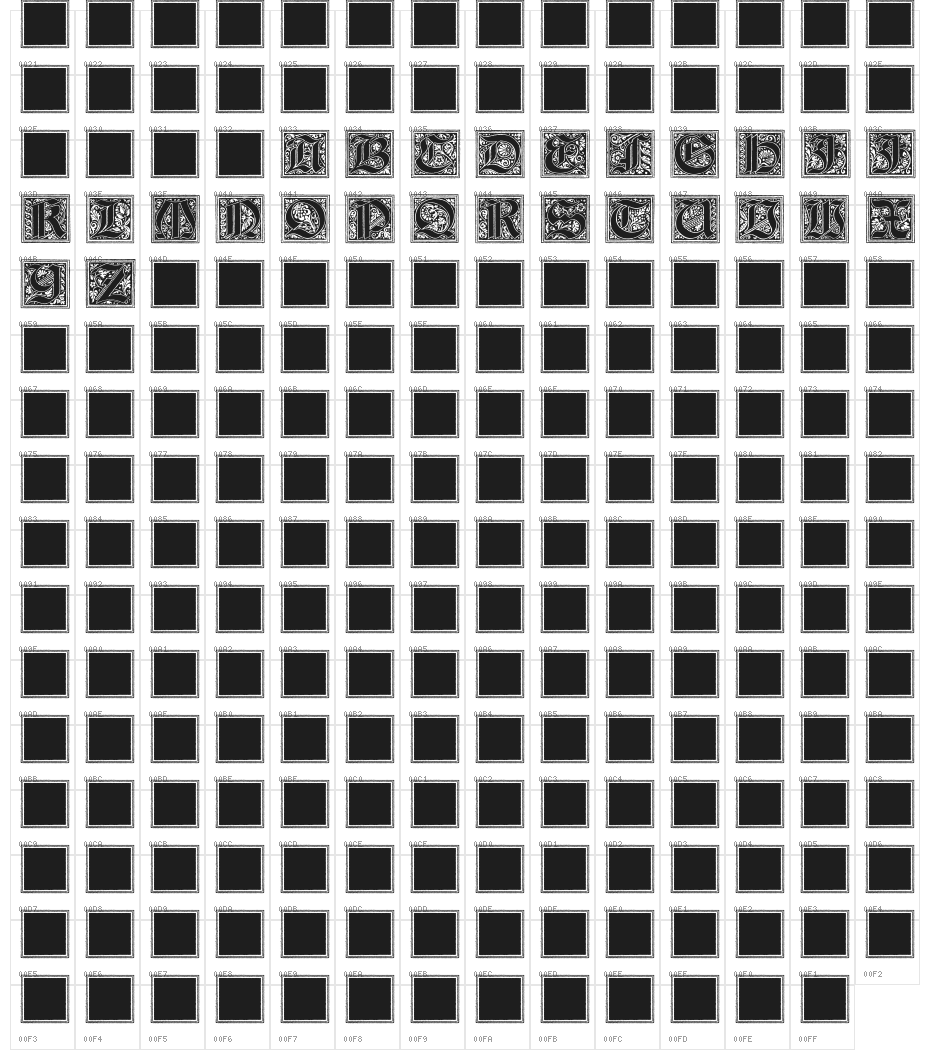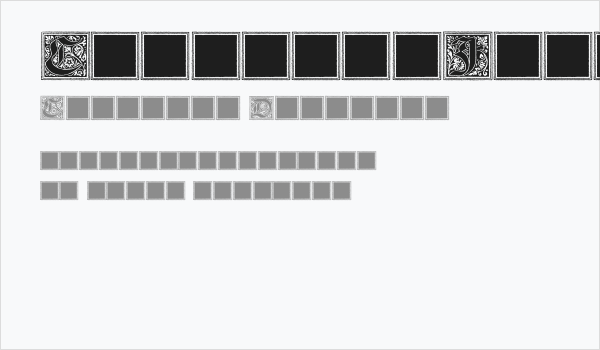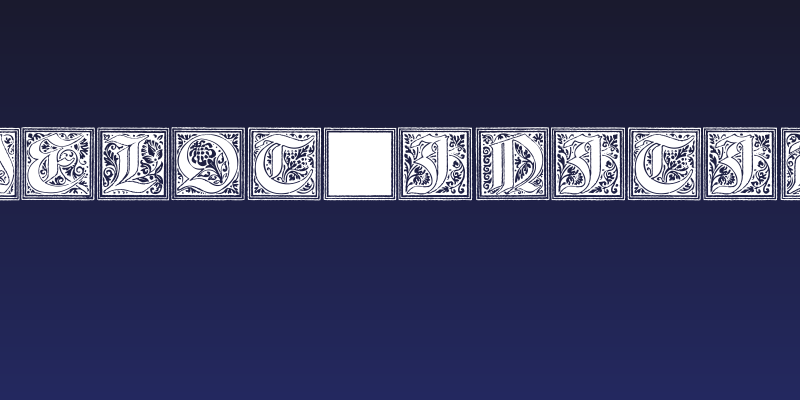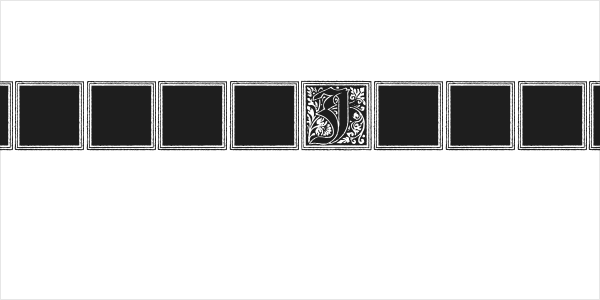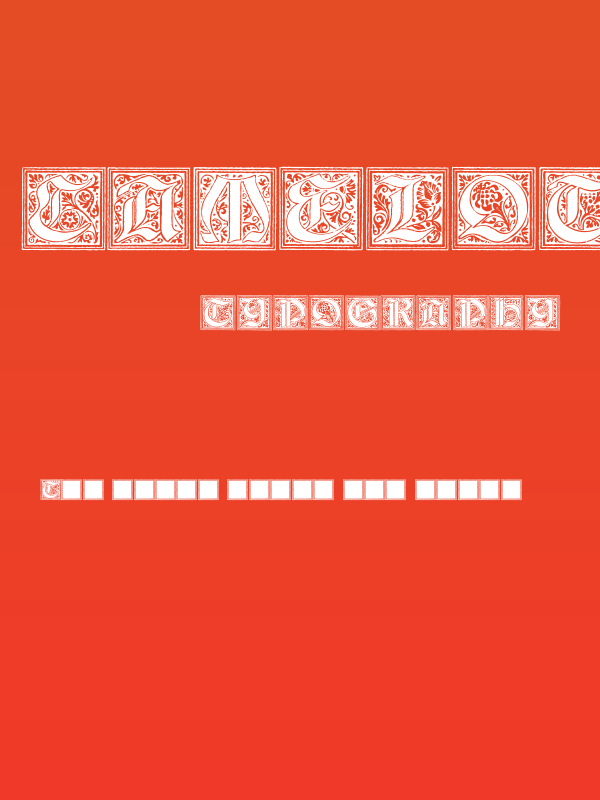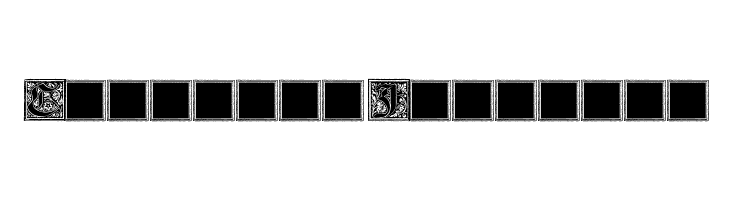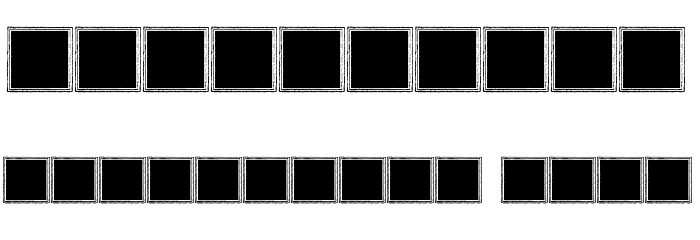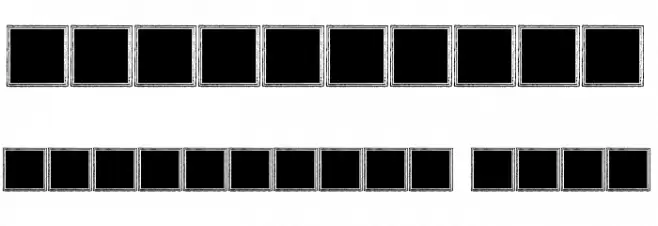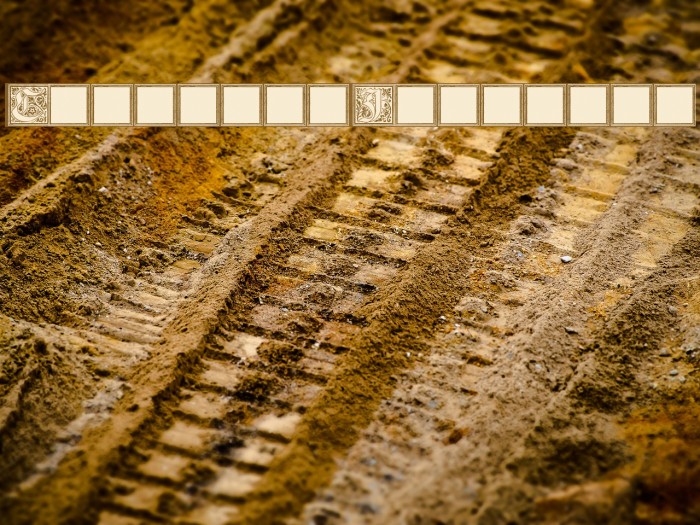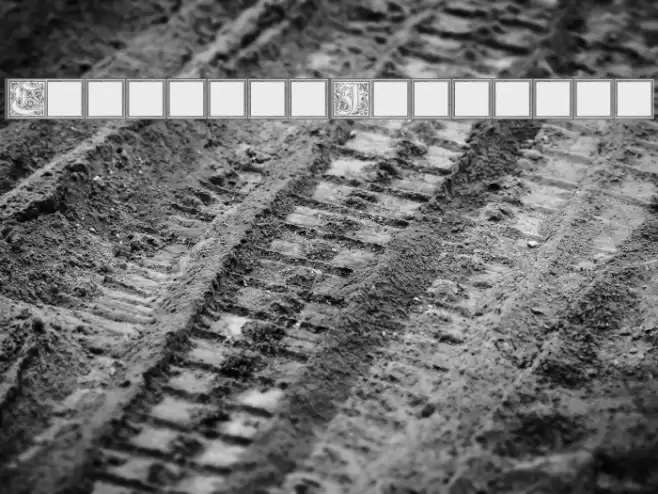
Camelot_Initials Font
✎ Gothic
Fonts by Paul Lloyd
| カテゴリ | Gothic |
| 用途 | Logos, Headlines, Decorative elements |
| おすすめプロジェクト | Ideal for use in historical-themed designs, book covers, invitations, or any project seeking a vintage or classical aesthetic. |